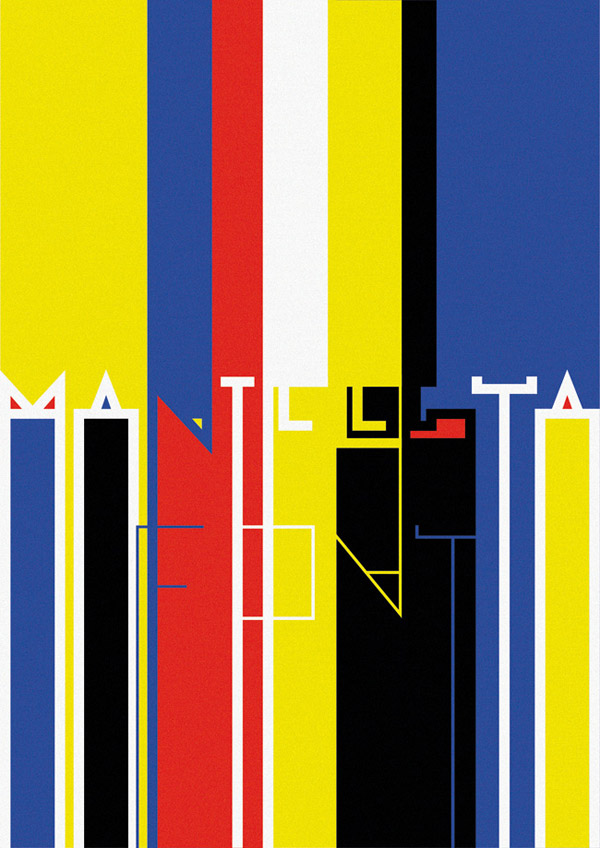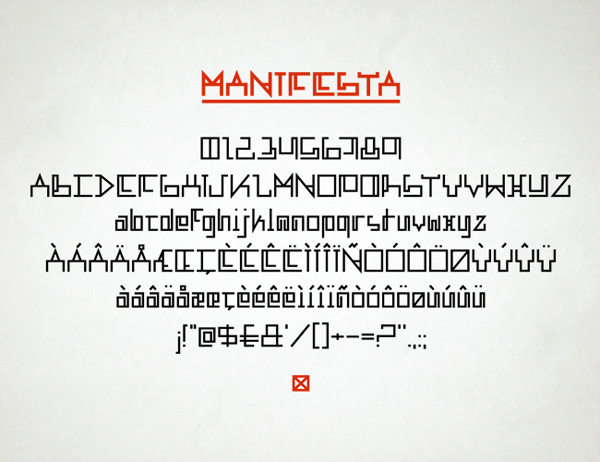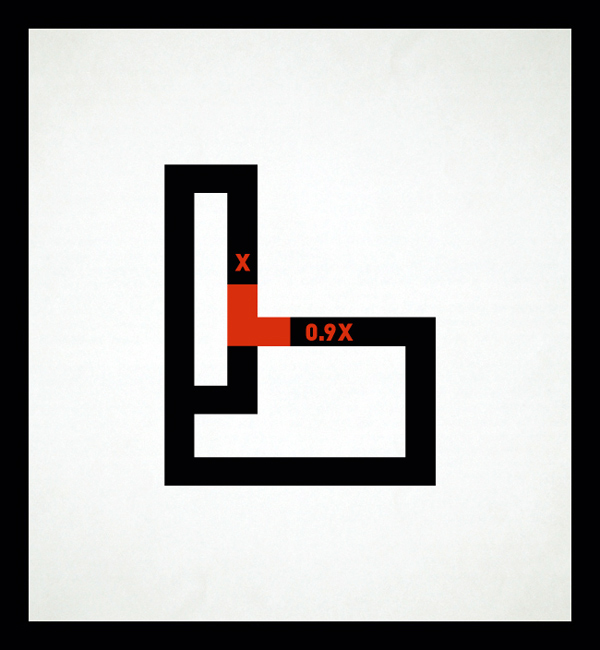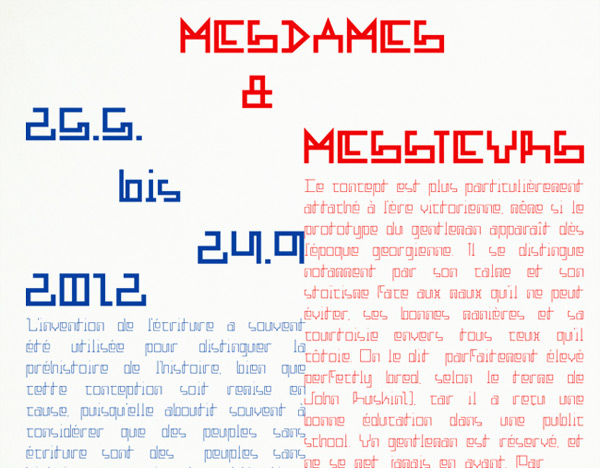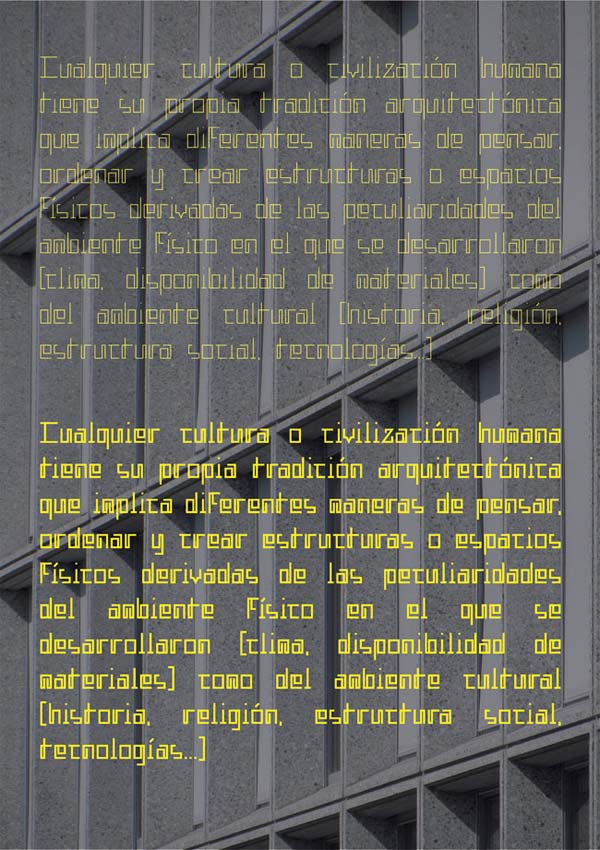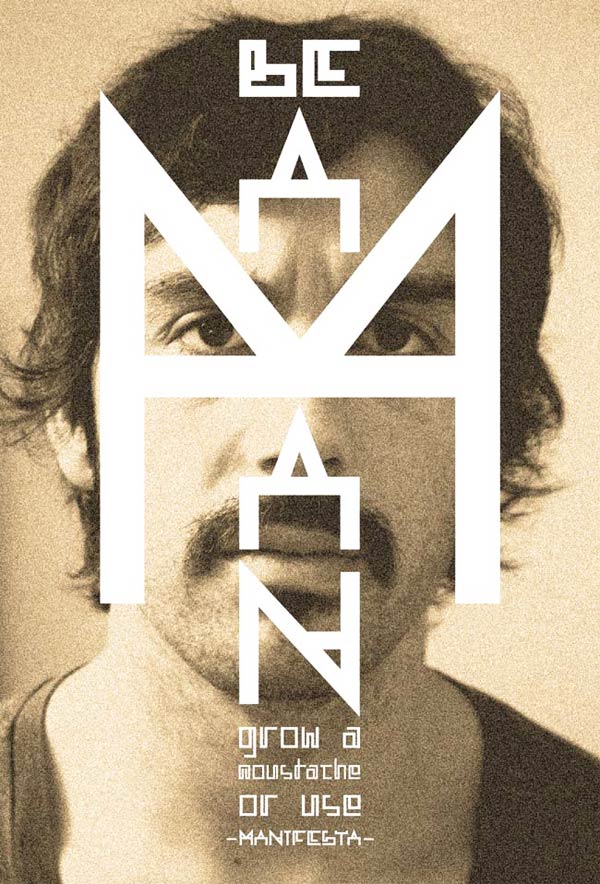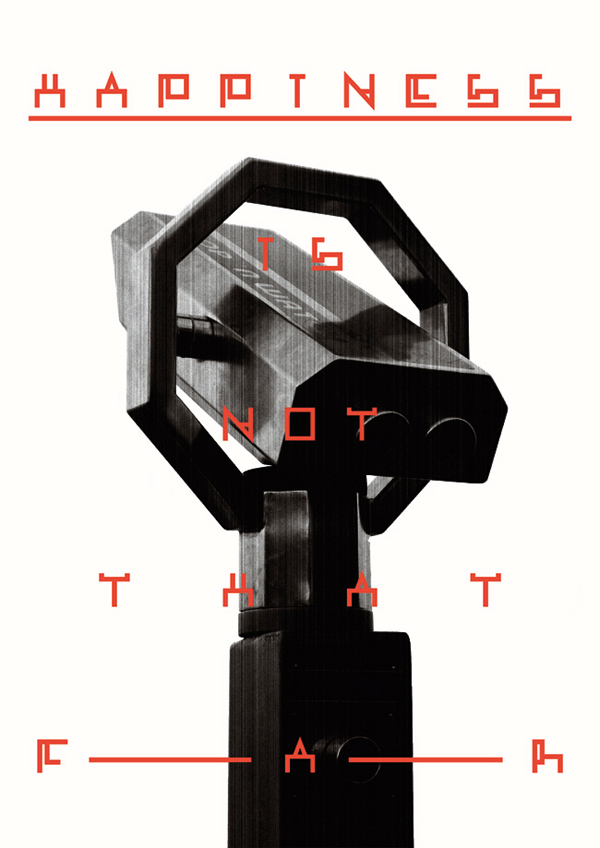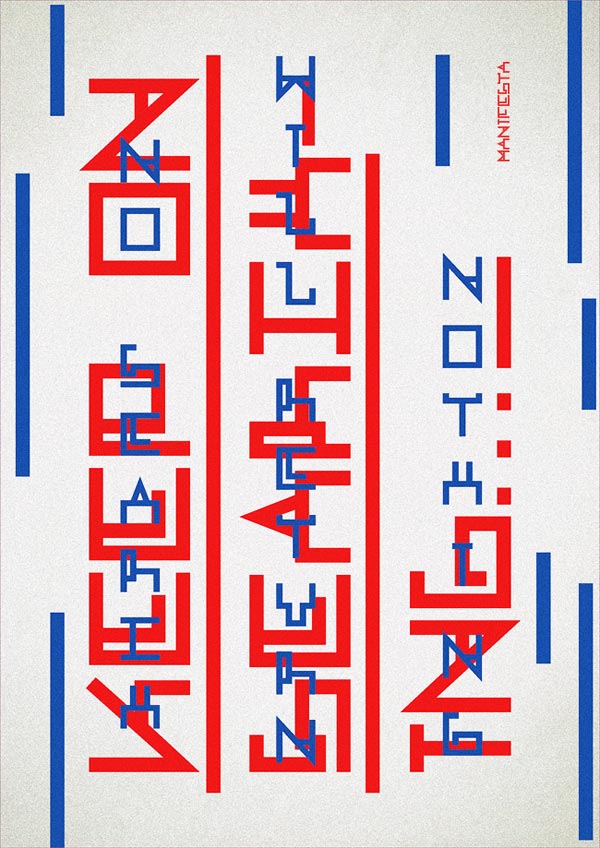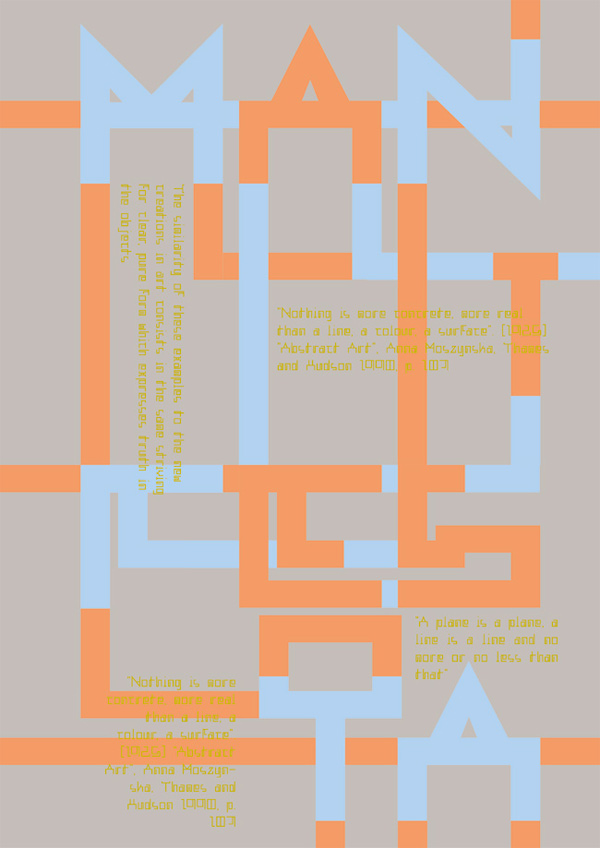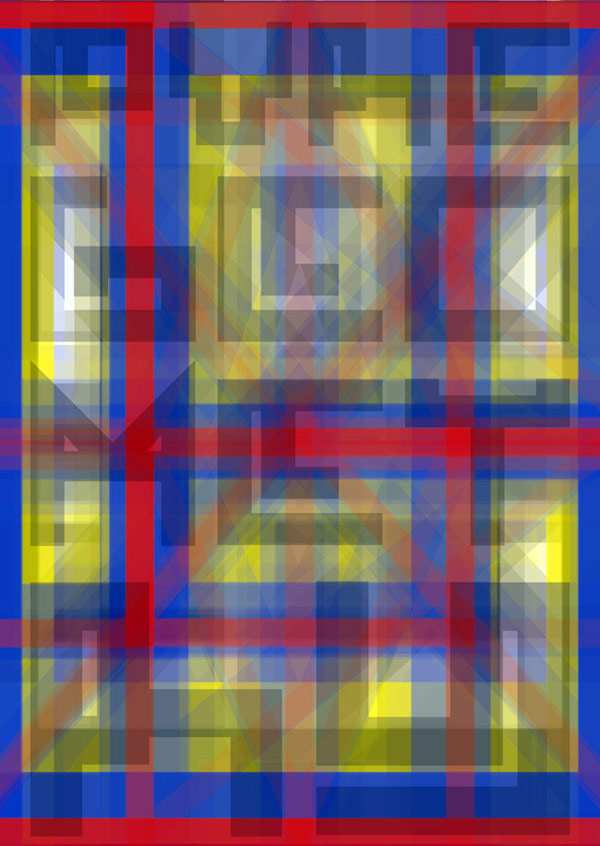
Manifiesta, tipografía geométrica de Fermín Guerrero
El joven diseñador uruguayo Fermín Guerrero propone con Manifesta una tipografía que examina las fronteras de la legibilidad a través de un trazo geométrico inspirado en los diseños de Max Kisman y en las propuestas vanguardistas de principios del siglo XX.
Aplicación tipográfica de Manifiesta, Fermín Guerrero, 2012.
Manifesta es descrita por su creador como una fuente display especialmente concebida para textos cortos y títulos. Cada uno de los tipos se desarrolla en líneas rectas de un grosor homogéneo. El diseñador ha querido explorar el potencial del trazo contínuo, de tal manera que los glifos parecen dibujados con un teleskecht.
Manifiesta, Fermín Guerrero, 2012.
Boceto, Manifiesta, Fermín Guerrero, 2012.
Grosor del glifo, Fermín Guerrero, 2012.
La tipografía está inspirada en los diseños geométricos de los movimientos vanguardistas de principios del siglo XX. Asimismo, reivindica el papel de Max Kisman, tipógrafo holandés pionero en el uso del ordenador.
Manifiesta, Fermín Guerrero, 2012.
La familia tipográfica está compuesta por cuatro pesos diferentes: ligera, regular, media y negrita. Cada una de las fuentes está disponible en caja alta y caja baja, e incluye signos diacríticos, números y signos ortográficos.
Aplicación gráfica de Manifiesta, Fermín Guerrero, 2012.
Los caractéres tienen una personalidad abstracta muy marcada, lo que crea una tensión entre la inteligibilidad y la propuesta artística: “[Manifesta] explora las relaciones entre las diferentes partes de la formas de las letras y la jerarquia, llevando al limite los limites de la legibilidad”, destaca el diseñador.
Caracteres, Manifiesta, Fermín Guerrero, 2012.